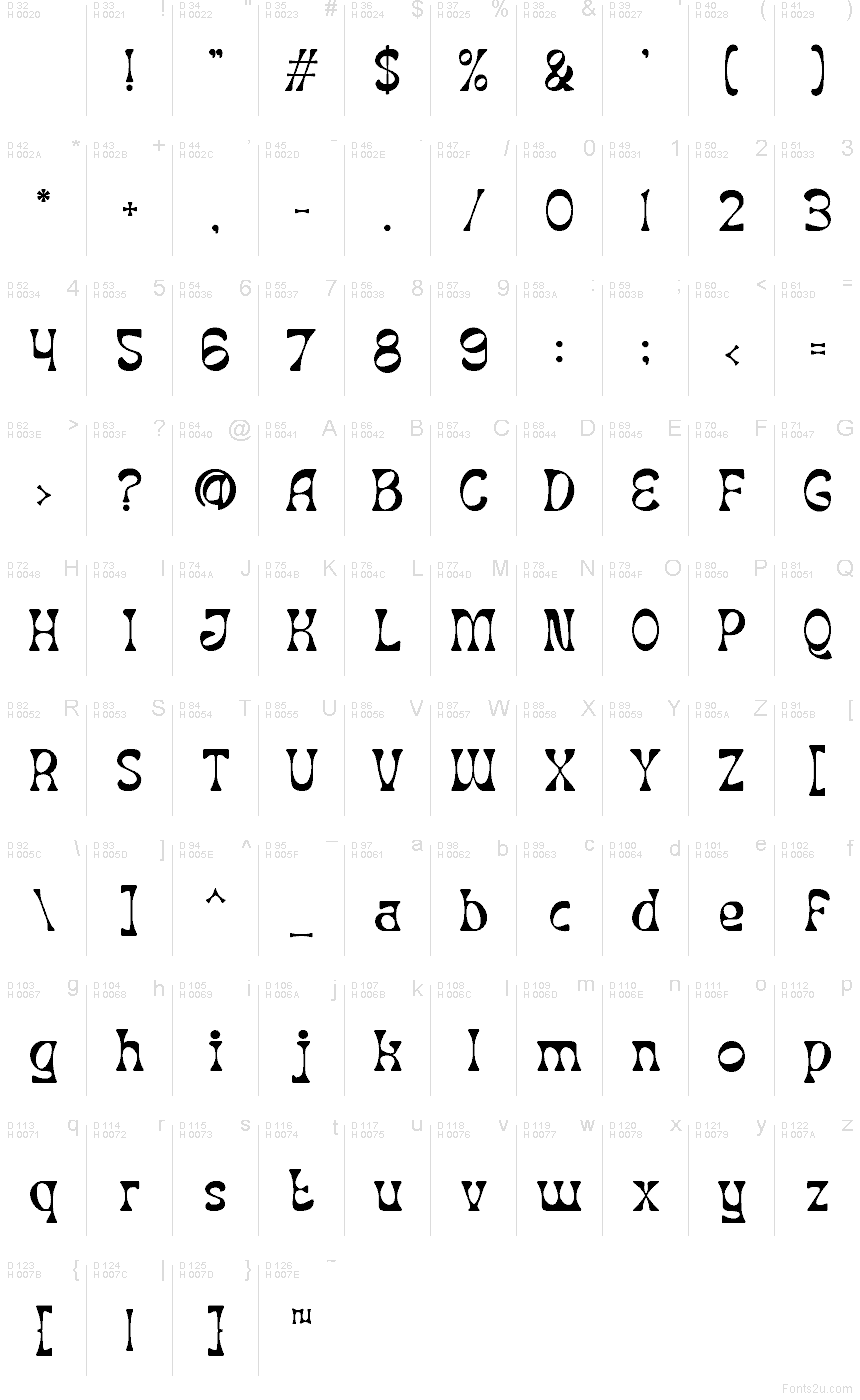
Mind Meld Two
Mind Meld Two di Putracetol Studio è un font display gratuito dallo stile groovy, caratterizzato da quell'atmosfera psichedelica tipica della fine degli anni '60. È costruito su curve bulbose, giunzioni strette e finali morbidi a goccia. Le lettere oscillano tra pienezza e leggerezza, conferendo al font un aspetto fluido e leggermente onirico, senza risultare mai troppo caotico.
È ideale per poster musicali, branding rétro, copertine di dischi, grafiche per festival e menù di caffè che richiedono calore e un pizzico di fascino surreale. Usalo per titoli brevi, scritte a effetto o loghi, poiché le curve sinuose e i dettagli a goccia rendono al meglio quando le lettere hanno spazio per respirare.